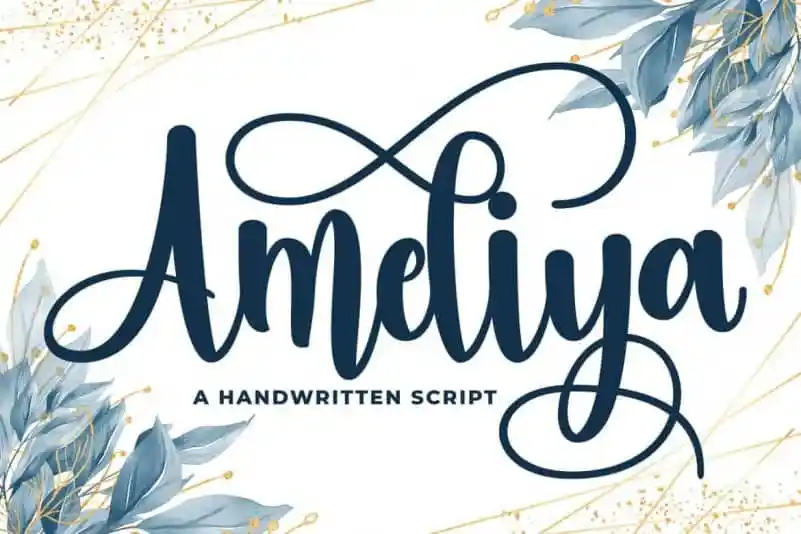
A Ameliya Script Font é uma elegante fonte para calligrafia manual que se destaca por sua simplicidade envolvente e beleza delicada. Com sua tipografia de texto limpa e feminina, essa fonte possui um ar sensual, glamouroso e de fácil leitura, especialmente favorecido pelo número considerável de ligações de letras delicadas e elaboradas. A Ameliya Script é perfeita para decorar agradáveis cartões de felicitações, postais artísticos belos, posts de mídia social chamativos e até mesmo convites de casamento que precisam ser cuidadosamente pensados em design. Engane-se se pensar que sua elegância não abrange o amor: você certamente vai cair rendido a esta fonte genuinamente linda.